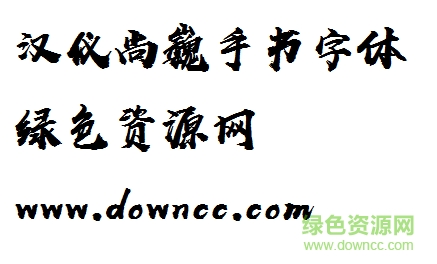
汉仪尚巍手书
汉仪尚巍手书ttf字体是一款汉仪类艺术风格十足的字体软件,手书体非常优雅大方,适用于海报标题印刷等行业,也深受广大书法家的喜爱,还有更多好看字体尽情期待,欢迎到绿色资源网下载体验!
汉仪尚巍手书字体是一款应用于艺术设计方面的简体中文字体,该字体笔画粗壮,尾部的甩尾有力且有丰富的笔触细节,大字效果突出且引人注目;并且最大程度还原作者书写字形,细节表现完整,且字库完整,可以广泛应用于名片设计、新闻媒体、宣传海报、ppt、影视制作以及内容用字等领域。